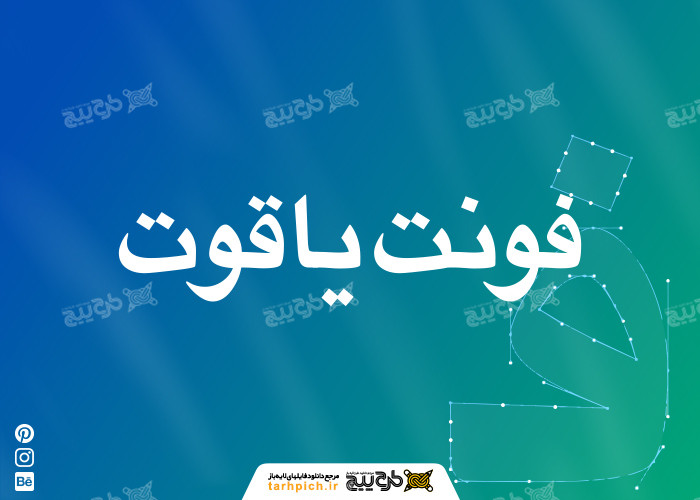
فونت یاقوت
فونت فارسی  یاقوت را می‌توان یکی از فونت‌های رایگان فارسی در نظر گرفت که کیفیت بالایی دارد. فونت یاقوت در دو نسخه بولد و ریگولار طراحی شده است. فونت یاقوت را می‌توان برای کارهای طراحی گرافیکی استفاده کرد. از ویژگی‌های این فونت می‌توان به قابلیت نصب روی سیستم عامل‌های مختلف حتی اندروید اشاره کرد.اگر به دنبال بهترین فونت فارسی برای خود هستید می توانید روی لینک کلیک کنید . از فونت یاقوت بیشتر برای طراحی بنرهای مذهبی، بنر شهادت، بنر اعیاد مذهبی  و بنرهای شعار سال استفاده می‌شود.اگر به دنبال طرح لایه باز برای فونت یاقوت هستید کافیست روی لینک مربوطه کلیک کنید.برای دانلود فونت رایگان روی لینک کلیک کنید.
طراح فونت یاقوت
فونت یاقوت را شرکت برنا رایانه طراحی کرده است